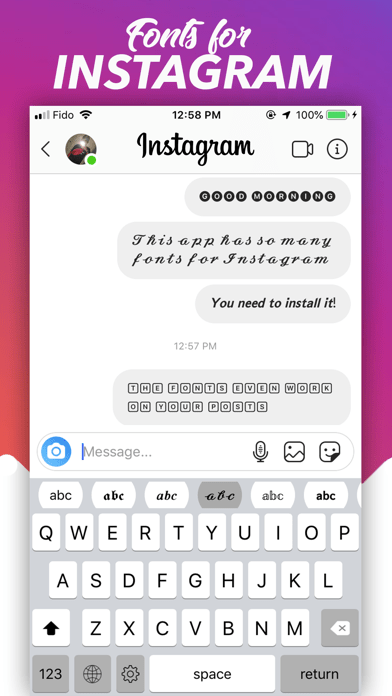
Как изменить шрифт Instagram (самый простой метод №1)
Изменить шрифт в Instagram несложно, и он действительно может выделить ваш профиль! Это действительно просто сделать, если у вас есть доступ к хорошему сменщику шрифтов в Instagram …
В наши дни у всех есть Instagram, поэтому выделиться из толпы становится все труднее и труднее. Ваша биография в Instagram — один из самых важных компонентов всей вашей страницы — это то, что большинство людей видят в первую очередь. По этой причине вам нужно сделать его как можно более привлекательным.
И один из самых простых способов сделать это — изменить шрифт Instagram по умолчанию и превратить его во что-то более индивидуальное и необычное. Однако вы не можете сделать это внутри Instagram изначально, поэтому вам нужно проявить немного творчества. Однако это достаточно просто, так что не волнуйтесь.
Как изменить шрифт в InstagramЧтобы изменить шрифт вашей биографии в Instagram (или внутри ваших сообщений), вам нужно будет использовать один из многих онлайн-генераторов шрифтов Instagram.
- Генератор шрифтов метатегов
- Шрифты Instagram
- Шрифты Insta
- Лингоджем
- Прохладный Символ
Что мы рекомендуем? Генератор шрифтов метатегов; это онлайн-приложение позволяет вам предварительно просмотреть, как будет выглядеть ваш шрифт, поэтому для нас это тот, который нужно использовать. Это экономит ваше время, так как вам не нужно постоянно переключаться между генератором шрифтов и вашим профилем, когда вы проверяете разные идеи.
Если вы используете iPhone или iPad, вы можете загрузить для этого специальное приложение; это называется Шрифты — Для Instagram. С этим приложение установлен, вы можете делать все на своем телефоне, и вам не нужно заморачиваться ни с одним из вышеперечисленных сайтов. Если вы используете iOS, это лучший способ изменить шрифт в вашей биографии в Instagram.
На Android? Используйте приложение Cool Fonts; По сути, это то же самое, что и Fonts — для Instagram.
Какой шрифт использует Instagram?Большинство людей никогда не задумываются о выборе шрифта. Но выбор шрифта, особенно при создании приложений и сайтов, которые обслуживают сотни миллионов пользователей в день, очень и очень важен — он может оказать огромное влияние на вовлеченность. Видите ли, есть определенные шрифты, которые люди, знают они это или нет, предпочитают читать онлайн.
Instagram использует шрифт под названием Neue Helvetica., небольшая вариация Helvetica почти для всего текста в приложении, то есть текст, который вы вводите и видите в своей биографии, в своих сообщениях и в сообщениях других людей. Neue Helvetica — красивый, легкий шрифт, который выглядит стильно, но приятен для глаз — это очень важно для онлайн-приложений и приложений.
Называется «Новая Гельветика».Всего более Веб-разработчикам доступно 650,000 XNUMX шрифтов. и приложений. Тем не менее, наиболее часто используемые шрифты, с которыми вы столкнетесь в Интернете, как правило, относятся к семейству веб-шрифтов Sans Serif. О, и если вам интересно, Sans Serifs — это французское слово, которое, грубо говоря, переводится следующим образом: «без линии и/или штриха».
И на данный момент это одни из самых популярных шрифтов без засечек, которые вы встретите в Интернете:
- Arial
- манометры
- Candara
- В. Готика
- Консоли
- Dejavu sans
- Франклин Готика
- Джилл Санс
- Helvetica
- Люцида Санс
- MS без засечек
- Новая Гельветика
- Optima
- Пользовательский интерфейс Segoe
- Tahoma
- Требушет М.
С. - Verdana
Опять же, довольно просто: перейдите в генератор метатегов на своем телефоне (или ПК, если вы работаете с компьютера), введите свой текст, найдите шрифт, который хотите использовать, нажмите «Копировать», а затем вставьте этот код в свою биографию в Instagram. Вот и все, готово!
Теперь все, что вам нужно сделать, это нажать «Сохранить», и ваша биография в Instagram теперь имеет новый модный шрифт. Все просто, правда?
Как мы уже отмечали выше, ваша биография в Instagram — один из самых важных аспектов вашей учетной записи. Это то, что люди видят в первую очередь, и это играет огромную роль в том, решит ли кто-то следовать за вами или нет.
Вам понадобится отличное изображение профиля, что-то, что действительно привлекает внимание, и хорошее, простое описание биографии. Здесь все должно быть просто, просто и по делу.
Вы хотите, чтобы ваша биография в Instagram была уникальной и точно передавала, о чем ваша страница. Если это бизнес-аккаунт, убедитесь, что MO вашего бизнеса находится в центре внимания — вы хотите поговорить о том, что отличает вас здесь. Убедитесь, что вы тестируете и другие BIOS;
If твой инстаграм является личным, вам нужно передать немного своей личности в описании биографии — что-то, что является вашим уникальным. Это может быть цитата, которая вам нравится, принцип, по которому вы живете, или что-то, во что вы твердо верите. В любом случае, он должен представлять, что люди получат, если последуют за вами…
В общем, если бы я был очень педантичным, этот сайт следовало бы назвать «псевдо-шрифты Instagram». Но нынешнее название понятно, оно красивое и короткое 🙂 Так или иначе, именно поэтому вы можете копировать и вставлять эти шрифты в Instagram.